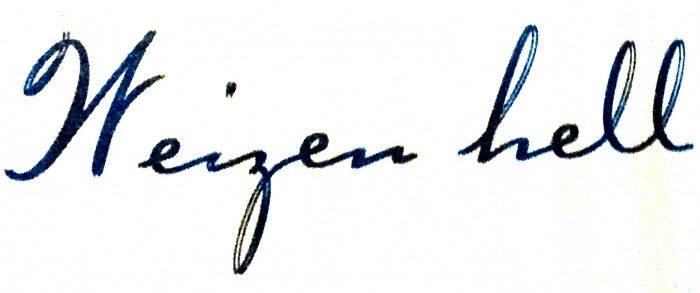
30er Jahre Schreibschrift für etikett gesucht
ich bin auf der suche nach dieser type.
stammt von einem alten Flaschenetikett
und jetzt soll sie ein revival erleben.
ist eindeutig satzschrift, nicht gezeichnet aber mit federstrich.